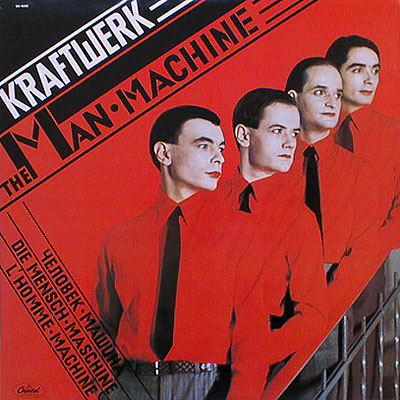
Welche Schriftart ist das ?
Ist mir auch egal ob er schlecht ist aber ich will ihn haben ;)
Weisst du welcher Font das ist ?
Geht es dir genau um diesen Font, oder darum, dass er unicase ist (Groß- und Kleinbuchstaben gleich hoch)?
Dann hilft schon eine suche bei myfonts.com um eine Auswahl zu bekommen. Vielleicht ist er da auch dabei, aber so wirklich lohnen tut es sich tatsächlich nicht...
mir geht es um den font ja.
Der Schwalbenkönig, das ist doch eine Maschine ...
eine menschmaschine?
Hallohallo, was ist denn jetzt los? Natürlich kann man nicht alle kennen, aber die paar … hmm … die immer wieder kommen.
Nachtrag: Und außerdem: Erstes Schriftenidentifizier-Geheimnis: Wenn's nicht innerhalb einer Stunde identifiziert ist, ist es mit einer 99,9%igen Wahrscheinlichkeit ein Free/Sharewarefont und mit 75%iger Wahrscheinlichkeit auf der gesperrten französischen Seite gelistet.